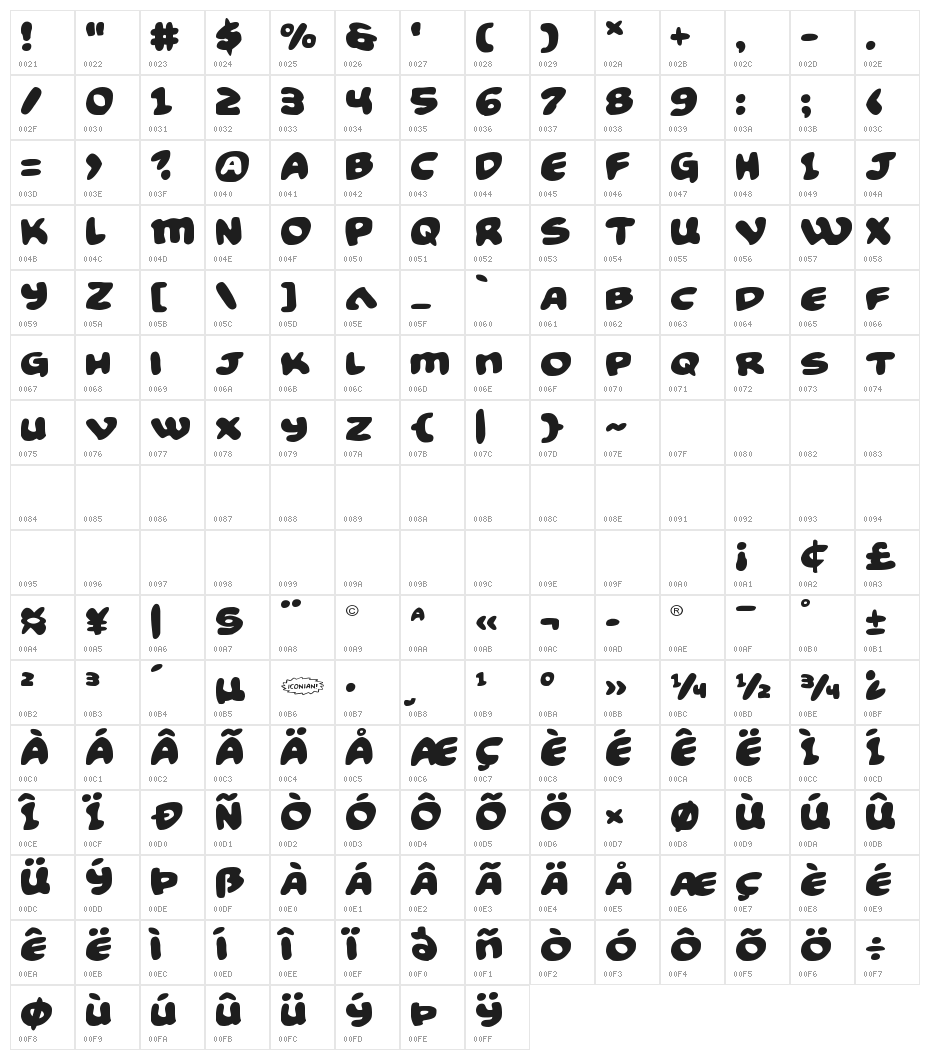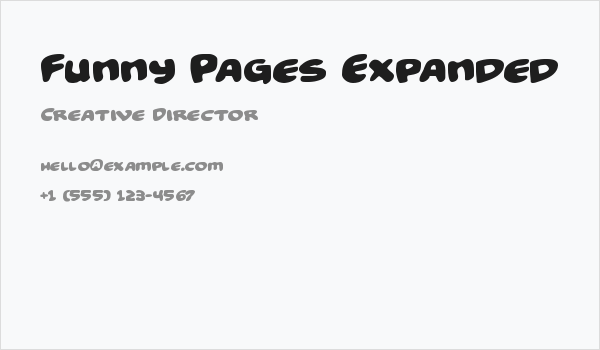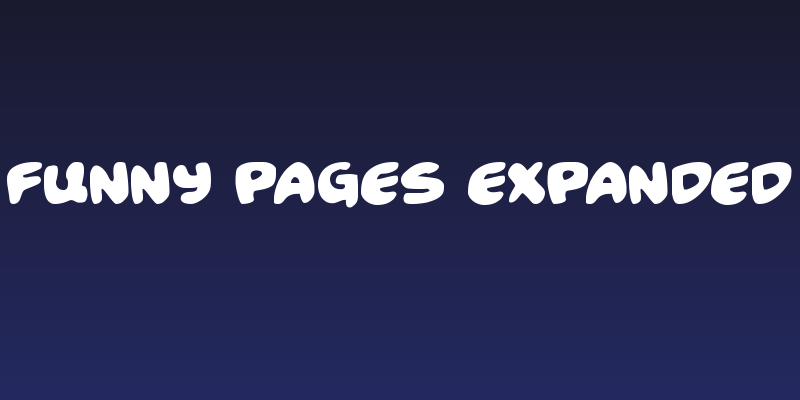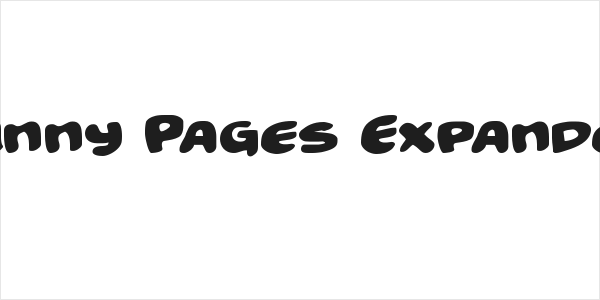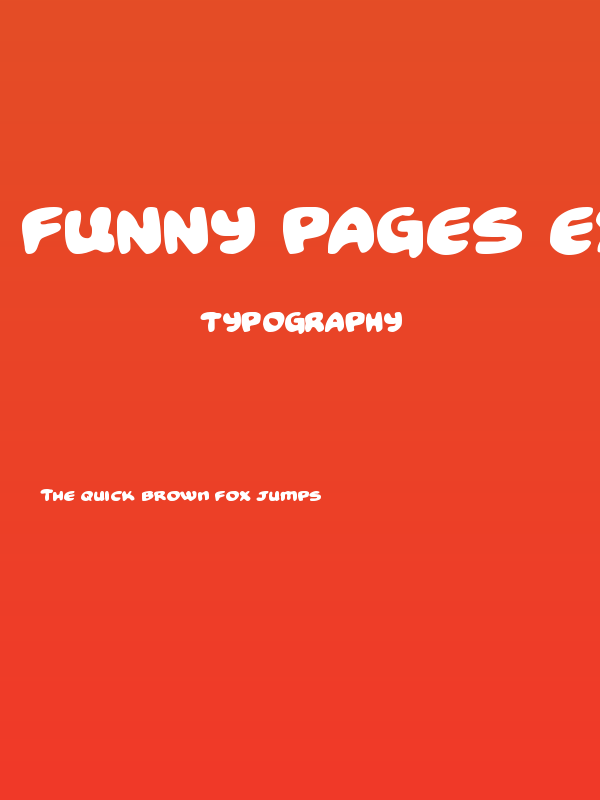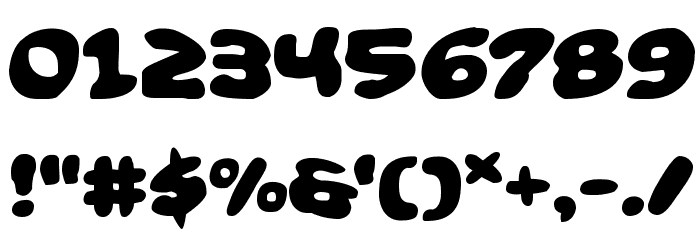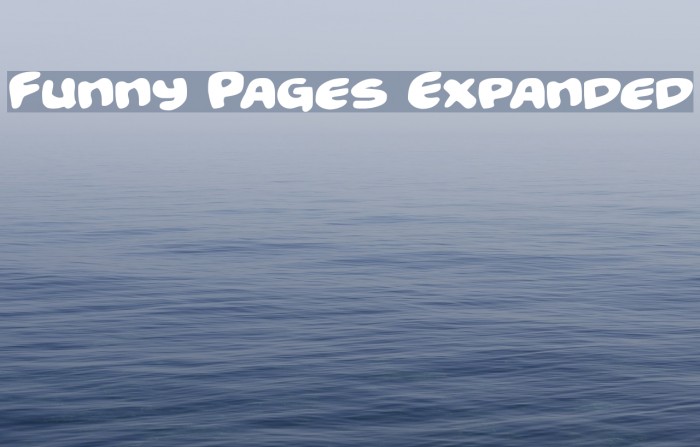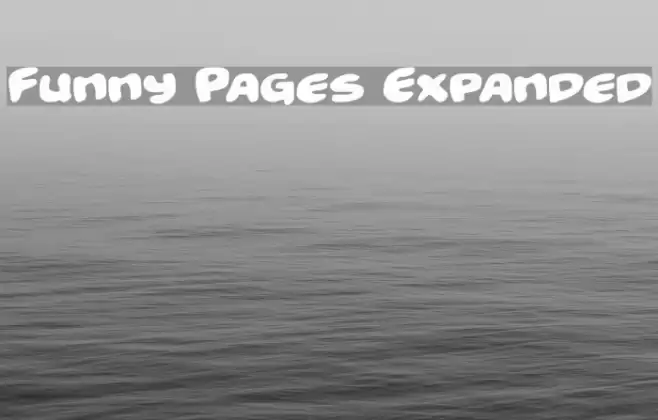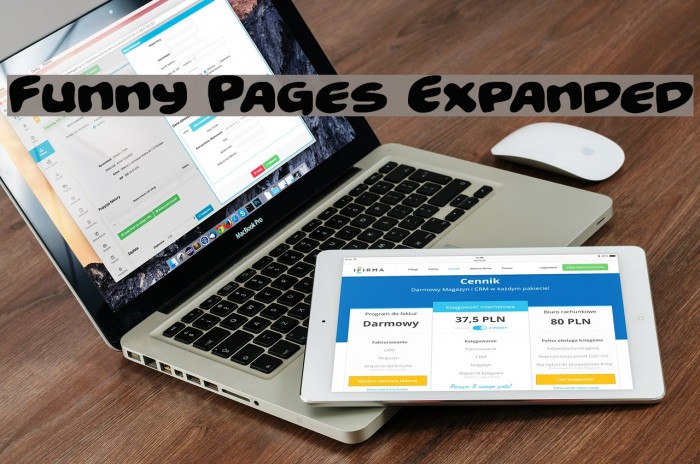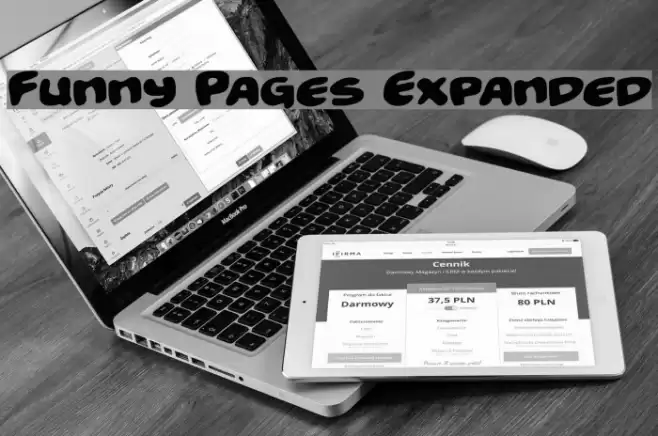
Funny Pages Expanded Font
| النمط العام | Playful, Fun, Cartoonish |
| مشاريع مقترحة | Ideal for children's books, comic strips, playful branding, party invitations, and any project requiring a lighthearted and engaging typeface. |